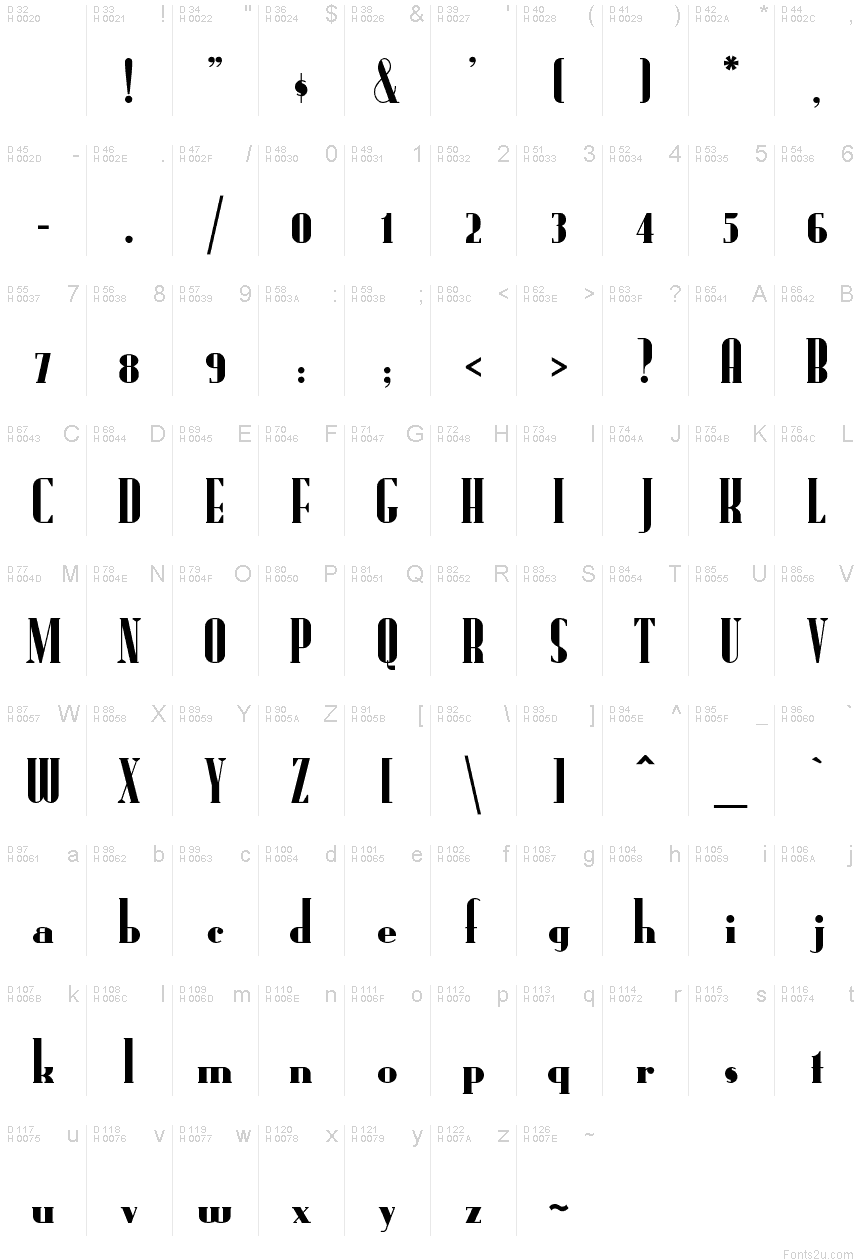
Radio Ranch od Nicka Curtisa to bezpłatny, szeryfowy krój Art Déco o wysokim, teatralnym rytmie wczesnych plakatów radiowych. Litery łączą w sobie niezwykle cienkie kreski, masywne piony i zaokrąglone misy, tworząc wyrazisty czarno-biały wzór. Całość jest elegancka, choć nieco ekstrawagancka, z wyraźnym klimatem epoki radia lat 20. i 30.
Ten bezpłatny font sprawdzi się w nagłówkach plakatów, okładkach magazynów, projektach w stylu retro, menu koktajlowych czy kartach tytułowych, wszędzie tam, gdzie klimat tamtych lat musi być wyczuwalny od pierwszego wejrzenia. Doskonale nadaje się również do monogramów i krótkich nazw – silny kontrast oraz wyprostowane, rzeźbiarskie formy sprawiają, że nawet kilka liter nabiera wyjątkowego charakteru.